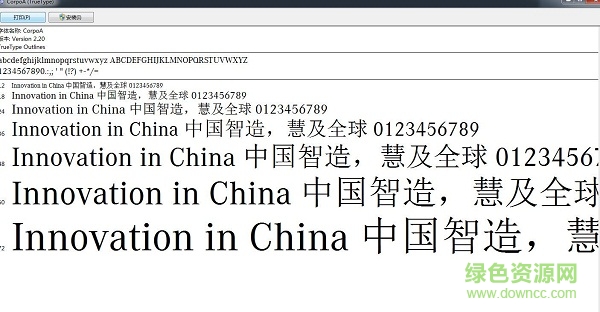
corpoa
corpoa字體是一款識(shí)別度非常好的襯線字體,氣質(zhì)典雅,字形沉穩(wěn),結(jié)構(gòu)清晰,粗細(xì)對(duì)比較為明顯,適合長(zhǎng)文閱讀,本站更多高品質(zhì)英文字體免費(fèi)提供,歡迎大家前來(lái)下載!
corpoa字體